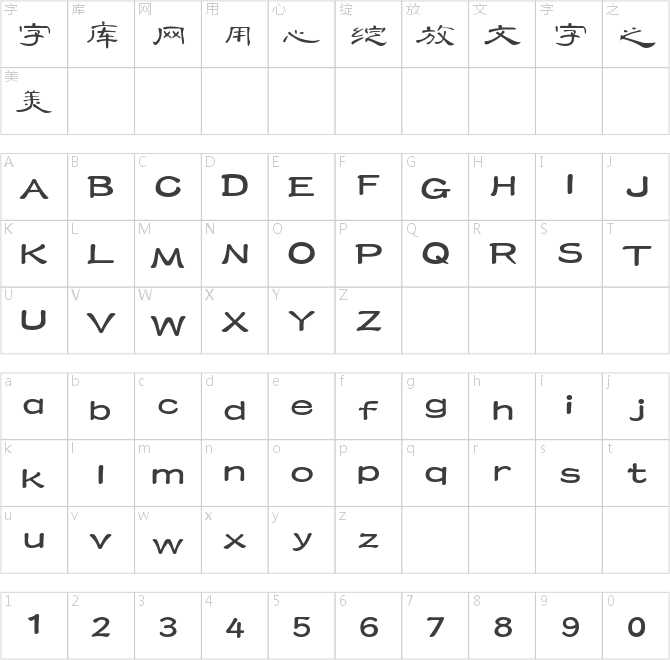
字體名稱: 三極曹全碑簡體
三極曹全碑簡體
《曹全碑》屬東漢末隸書完全成熟期的代表作品之一,它記載了東漢末年曹全鎮壓黃巾起義的事件,是研究東漢末年農民起義重要的歷史資料,也是現存中國漢代石碑中保存比較完整、字體比較清晰的少數作品之一。其結字勻整,用筆方圓兼備,而以圓筆為主,風致翩翩,美妙多姿,是漢隸中秀美風格的代表。